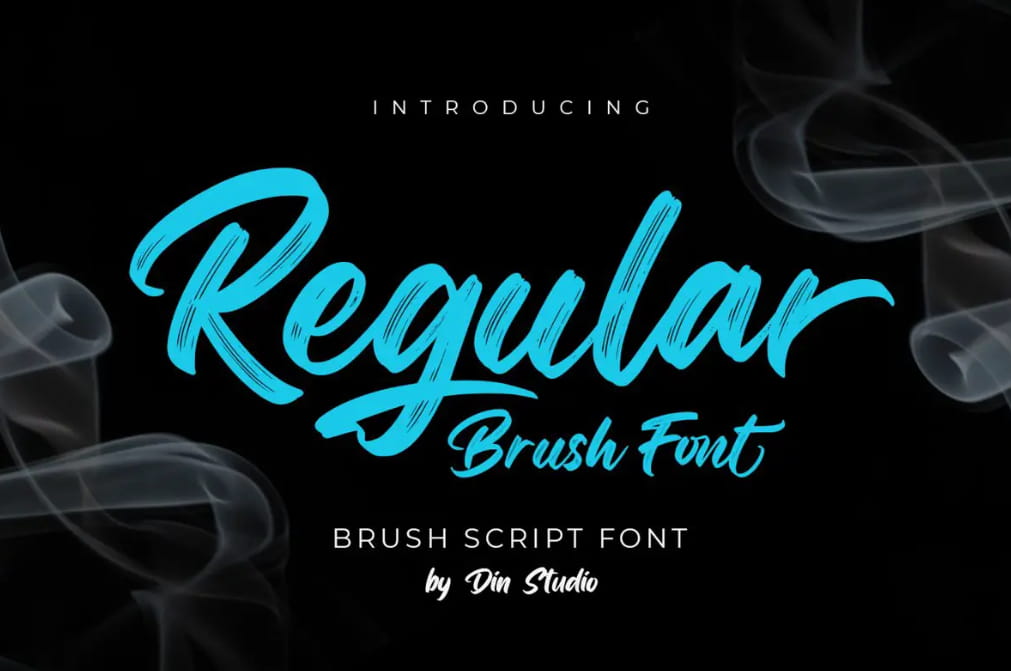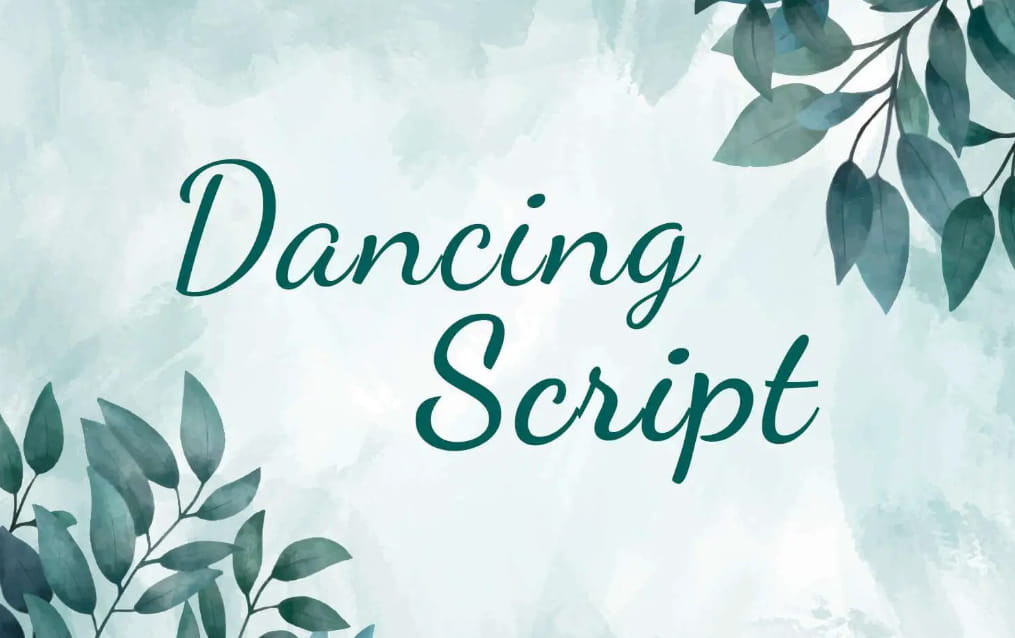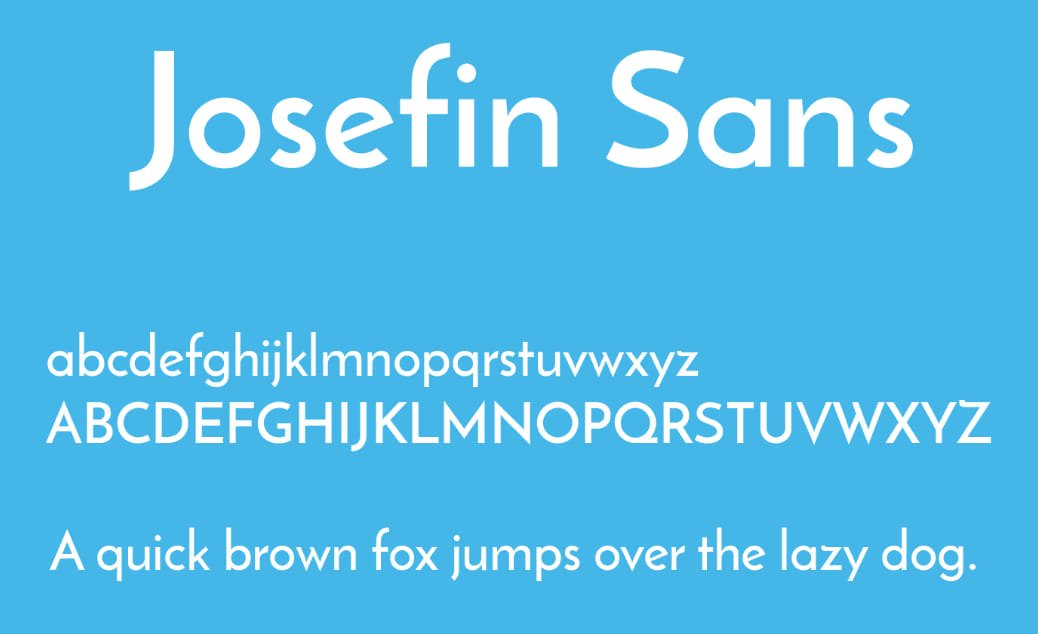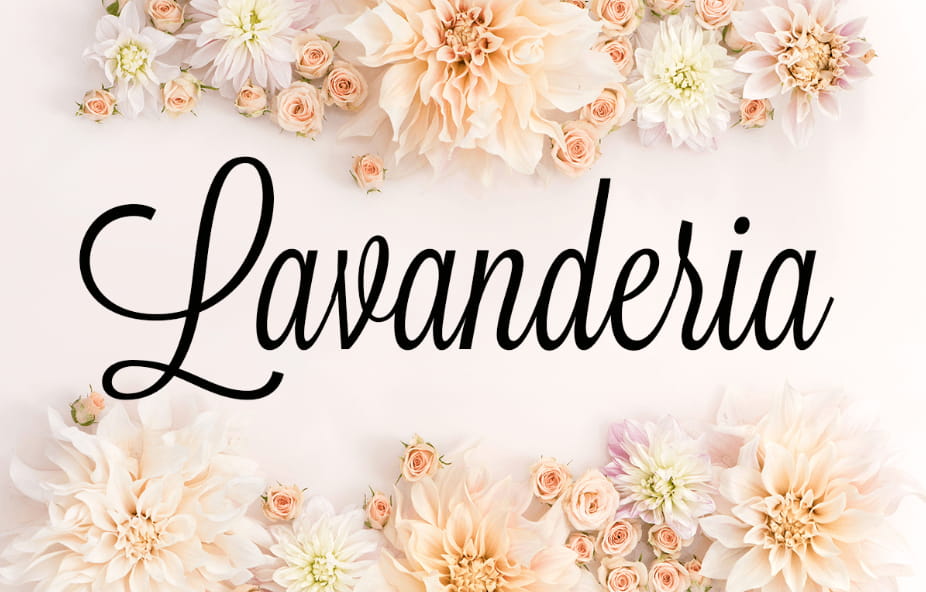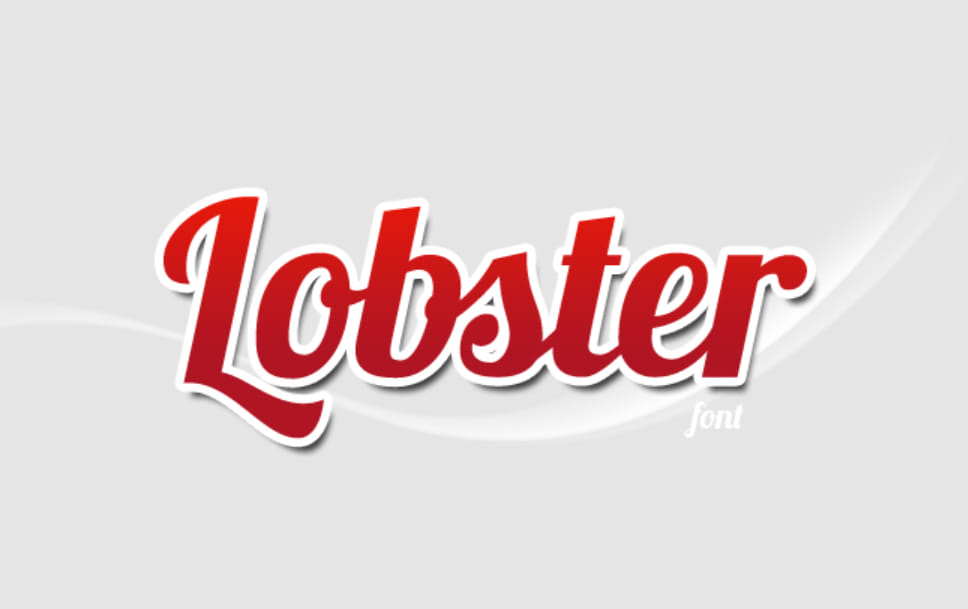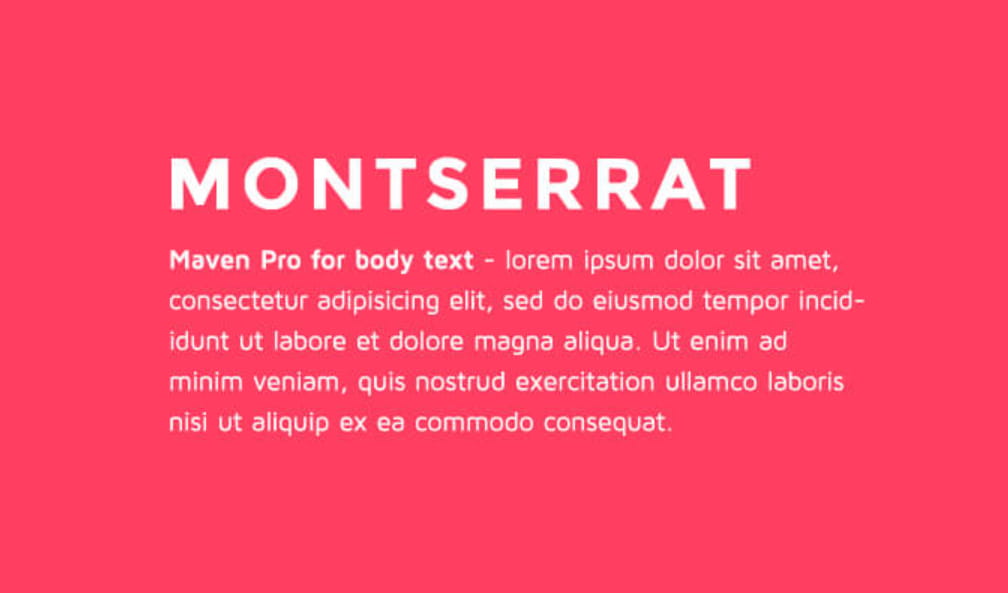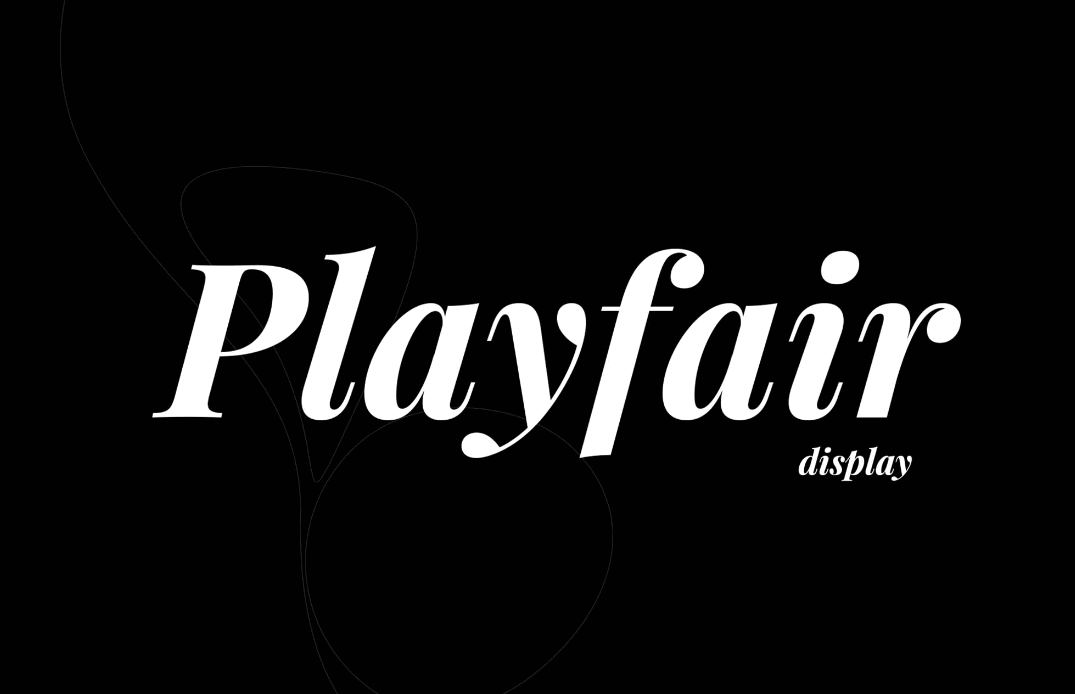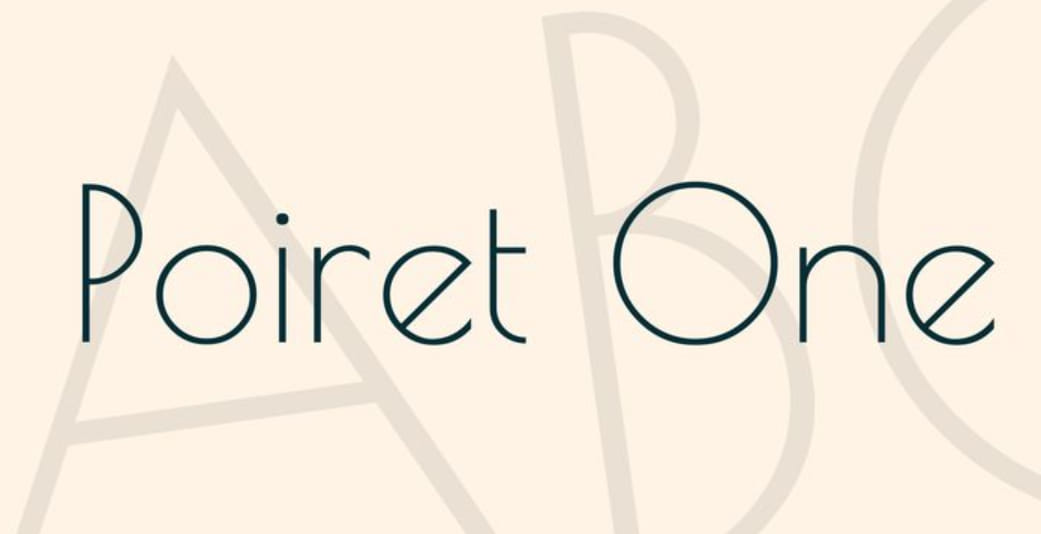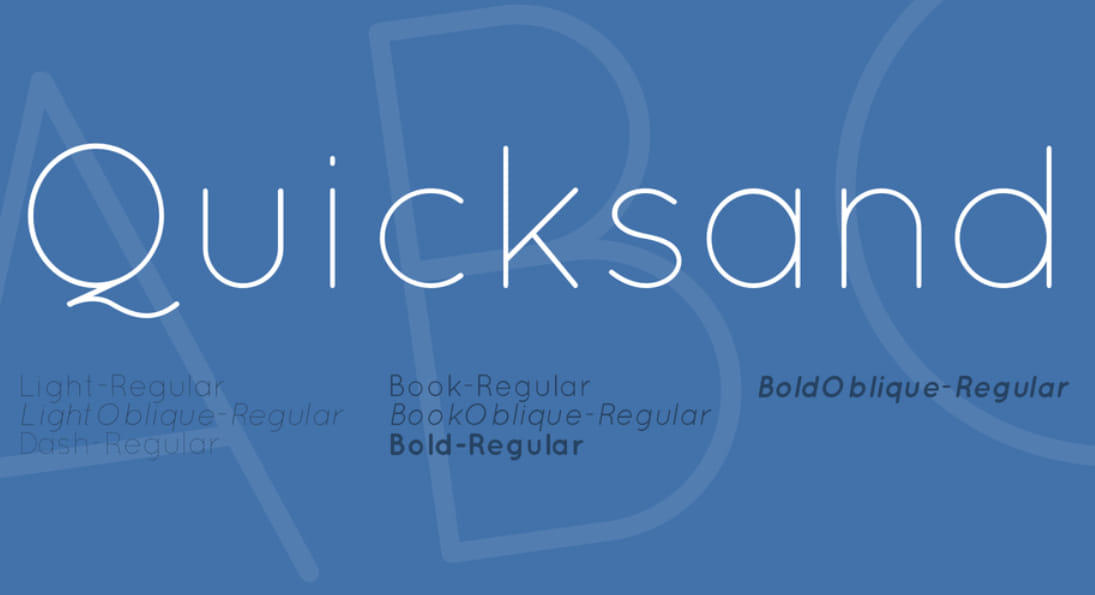
17 Jenis Font Undangan Pernikahan untuk Hari Spesial Anda
Jenis Font Undangan Pernikahan
Dalam merencanakan pernikahan, setiap detail penting berkontribusi dalam menciptakan momen yang tak terlupakan. Salah satu detail yang sering kali mendapat perhatian khusus adalah pemilihan font untuk undangan.
Font yang dipilih tidak hanya mencerminkan gaya dan kepribadian Anda sebagai pasangan tetapi juga menetapkan tema untuk acara tersebut.
Artikel ini akan mengajak Anda dalam memilih 17 jenis font undangan pernikahan yang sempurna untuk menambah sentuhan spesial pada hari besar Anda.
1. Alex Brush: Kesan Romantis dan Elegan
Diawali dengan “Alex Brush,” kreasi dari TypeSETit, font ini menawarkan gaya script yang elegan. Ini adalah pilihan tepat bagi pasangan yang menginginkan undangan dengan nuansa romantis dan anggun.
Gaya tulisan tangan yang lembut dari Alex Brush menambah kehangatan dan personalisasi pada setiap undangan.
2. Great Vibes: Keindahan Kaligrafi yang Mengalir
Selanjutnya ada “Great Vibes,” juga karya TypeSETit. Font ini memancarkan keindahan kaligrafi dengan alirannya yang mengalir bebas.
Great Vibes adalah pilihan yang ideal bagi Anda yang menginginkan undangan dengan gaya tangan alami yang berkelas. Estetika tulisan ini cocok untuk menciptakan suasana yang mewah dan elegan.
3. Pacifico: Gaya Kasual yang Menawan
Font Pacifico dikembangkan oleh Vernon Adams dengan gaya script yang lebih kasual. Font ini sempurna bagi pasangan yang ingin menampilkan sisi santai dan hangat pada undangan mereka.
Dengan karakter yang unik dan mudah dibaca, Pacifico menawarkan pendekatan yang lebih santai namun tetap menarik untuk undangan pernikahan Anda.
4. Snell Roundhand: Sentuhan Klasik
Selanjutnya adalah Snell Roundhand. Jenis font ini memiliki suasana klasik dan tradisional. Snell Roundhand cocok untuk pasangan yang menghargai desain timeless dan keanggunan abadi. Karakteristik hurufnya yang khas menghadirkan nuansa vintage ke dalam desain undangan Anda.
5. Bickham Script: Elegan dan Mewah
Bickham Script dikenal dengan keeleganannya yang mewah. Font ini ideal untuk undangan yang ingin menonjolkan keanggunan dan kemewahan. Detailnya yang rumit menunjukkan kualitas dan perhatian terhadap detail.
6. Quicksand: Modern dan Minimalis
Untuk pasangan yang menginginkan tampilan yang lebih modern dan minimalis, “Quicksand” adalah pilihan yang sempurna. Dengan garis-garis bersih dan bentuk yang sederhana, font ini memberikan kesan kontemporer pada undangan Anda.
7. Lavanderia: Sentuhan Artistik
Font Lavanderia dengan gaya brush yang artistik, membawa nuansa kreatif dan unik. Jenis font ini merupakan pilihan terbaik untuk pasangan yang mencari sesuatu yang berbeda dan menonjol.
8. Brush Script: Kasual dan Bersahaja
Font Brush Script menawarkan gaya tulisan tangan yang kasual dan bersahaja. Cocok untuk undangan yang ingin menghadirkan suasana santai namun tetap elegan.
9. Dancing Script: Dinamis dan Menyenangkan
Dancing Script adalah jenis font yang dinamis dan menyenangkan, sempurna untuk pasangan yang ingin menampilkan sisi ceria dan penuh semangat pada undangan tersebut.
10. Playfair Display: Klasik dengan Sentuhan Modern
Playfair Display menggabungkan keanggunan klasik dengan sentuhan modern. Font ini sangat cocok untuk undangan yang ingin menampilkan keeleganan dengan cara yang kontemporer.
11. Lobster: Berani dan Menarik
Lobster sangat menonjol dengan karakternya yang berani dan menarik. Font ini sangat cocok untuk pasangan yang ingin undangan mereka menjadi pusat perhatian.
12. Allura: Lembut dan Mengalir
Font Allura memberikan kesan yang lembut dan mengalir, ideal untuk menciptakan suasana romantis dan elegan.
13. Josefin Sans: Geometris dan Stylish
Setelah font Allura, ada lagi font yang bernama Josefin Sans. Font ini memiliki tampilan yang geometris dan stylish, cocok untuk pasangan yang mencari desain undangan yang modern dan bersih.
14. Amatic SC: Quirky dan Personal
Untuk suasana yang lebih personal dan quirky, “Amatic SC” adalah pilihan yang tepat. Font ini unik dan menambah sentuhan personal yang hangat pada undangan.
15. Montserrat: Elegan dan Serbaguna
Montserrat adalah font yang serbaguna dan elegan, sempurna untuk berbagai gaya undangan, dari modern hingga tradisional.
16. Poiret One: Art Deco dan Menawan
Poiret One yang terinspirasi dari art deco memiliki tampilan gaya yang menawan dan berkelas. Pilihan ini cocok untuk pasangan yang mencari sesuatu yang vintage namun tetap chic.
Penutup
Dengan berbagai pilihan font undangan pernikahan yang telah kita bahas, Anda dapat menemukan gaya yang paling sesuai dengan tema dan nuansa pernikahan Anda.
Ingat, undangan adalah salah satu kesan pertama yang akan diterima tamu tentang pernikahan Anda, jadi pilihlah font yang mencerminkan cinta dan kepribadian Anda sebagai pasangan.